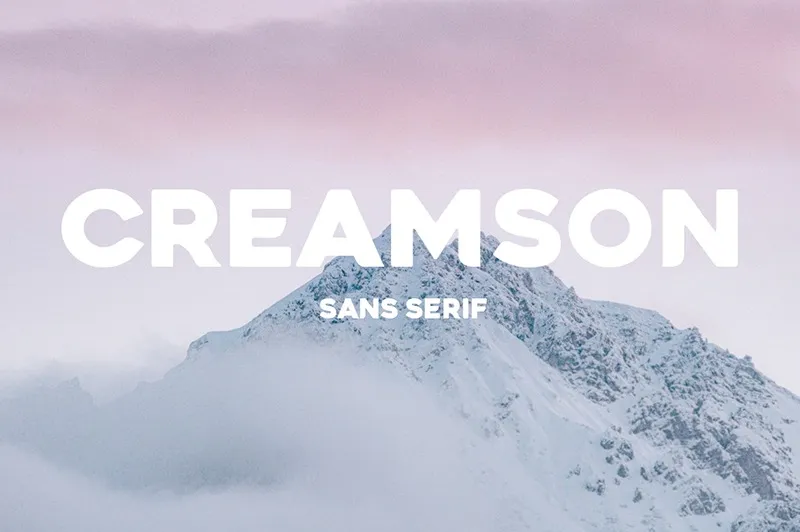
A Creamson Font é uma escolha ideal para aqueles que buscam um estilo moderno e geométrico no seu design visual. Manufacturada pela The Branded Quotes, essa fonte sans serif apresenta traços definidos e curvas perfeitamente alongadas, criando um equilíbrio entre seriedade e suavidade. O resultado é uma opção fresca para projetos que requerem impacto visual, mas valorizam também a delicadeza em seu aspecto final. Com suas linhas claras e formas geométricas perfeitamente curvadas, a Creamson oferece um toque de sofisticação sem perder sua força inegável. Este design foi criado pelo site de concursos 99designs, garantindo uma vasta variedade de opções para designers que buscam complementar suas criações com o certo estilo visual.